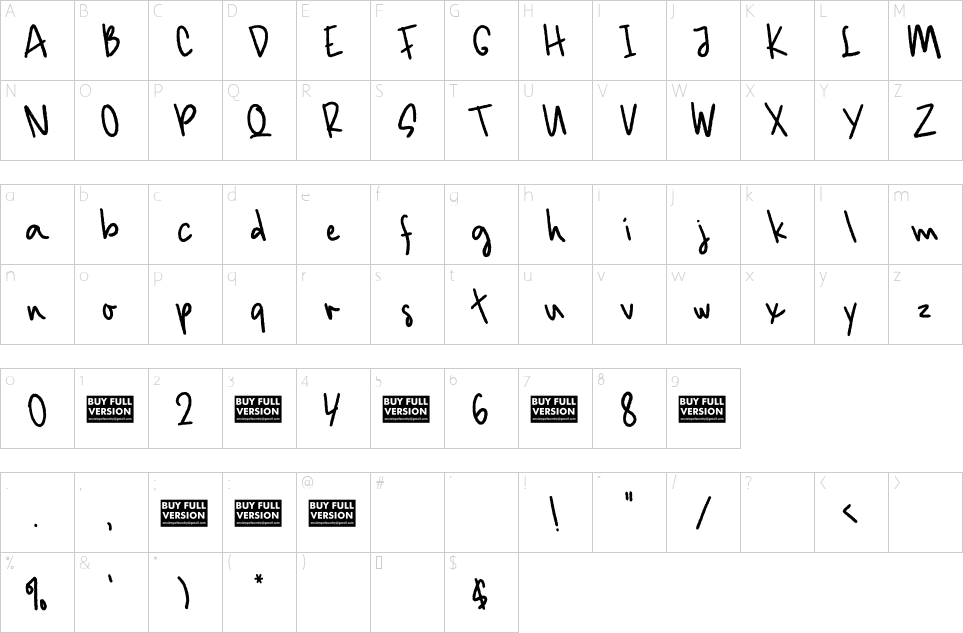
Aqui está uma descrição em português do Brasil para a página de download da fonte ‘Grateful Dead Font’, seguindo as instruções: A fonte Grateful Dead é um encantador remanescente das letras dos lendários shows que marcaram os anos 70 com o grupo musical espetacular do mesmo nome. Desenhada pela Anxietype Foundry, essa fonte se destaca por sua simplicidade e sofisticação ao mesmo tempo — ideia perfeita para aquelas criações de design que exigem uma paleta de letras única. A Grateful Dead Font é ideal tanto para projetos digitais como impressos. Seja em seu formato de código para Windows, Mac ou outro sistema operacional, ela se destaca por suas linhas elegantes e legíveis. Para quem busca adicionar um toque especial a qualquer projeto de design gráfico ou web, o Grateful Dead é uma fonte perfeita. Com um visual que evoca os grandes shows da década passada dos anos 70, essa fonte não só se destaca pela sua beleza única, mas também pelo fato de ser completamente gratuita. Essa fonte já foi baixada mais de 271 vezes e, graças a seu design cuidadoso e fácil de usar, deve tornar-se um dos favoritos dos designers. Além disso, a Grateful Dead é uma ótima escolha para projetos que exigem uma paleta de letras diversificada. Com uma combinação perfeita de sofisticação e simplicidade, a fonte Grateful Dead certamente trará um toque especial a qualquer projeto, tornando-a um tesouro valioso para quem busca recursos gráficos gratuitos.